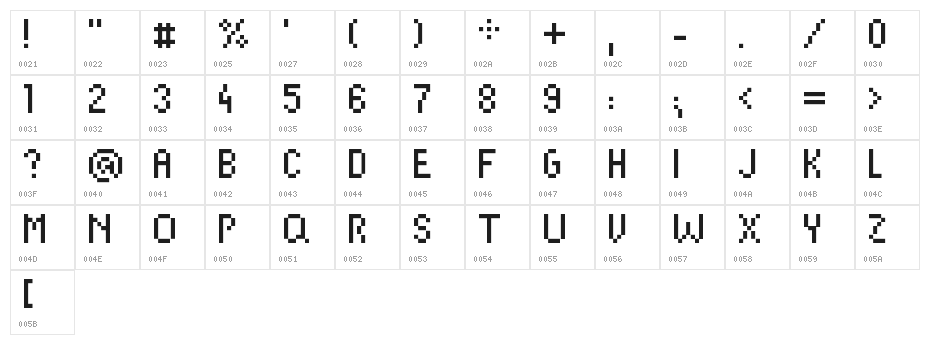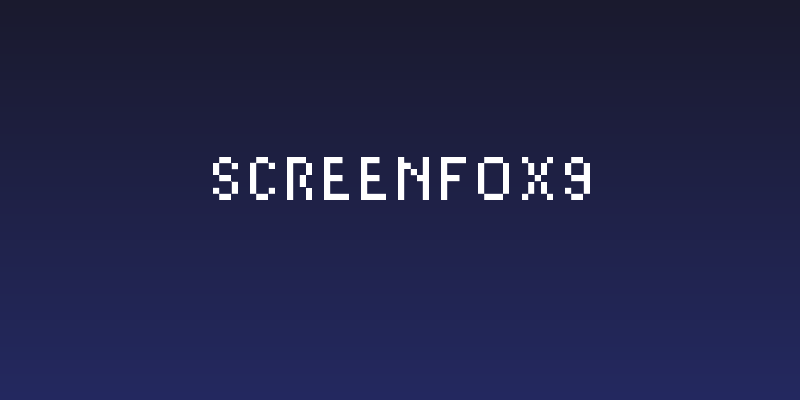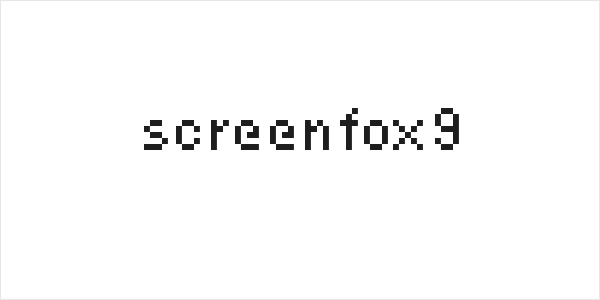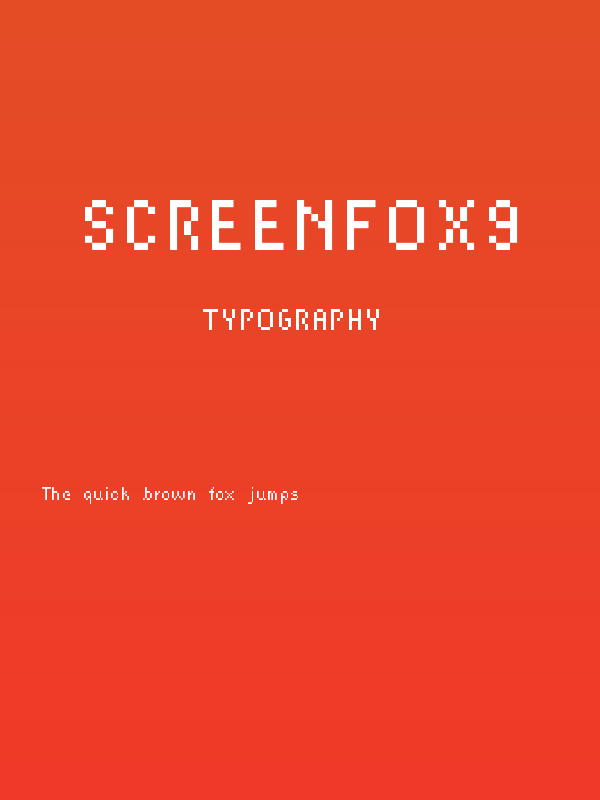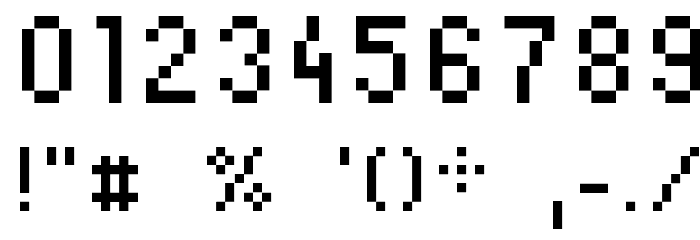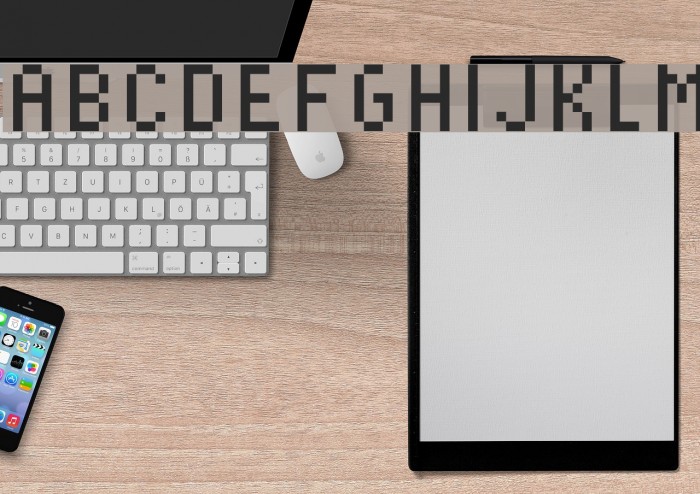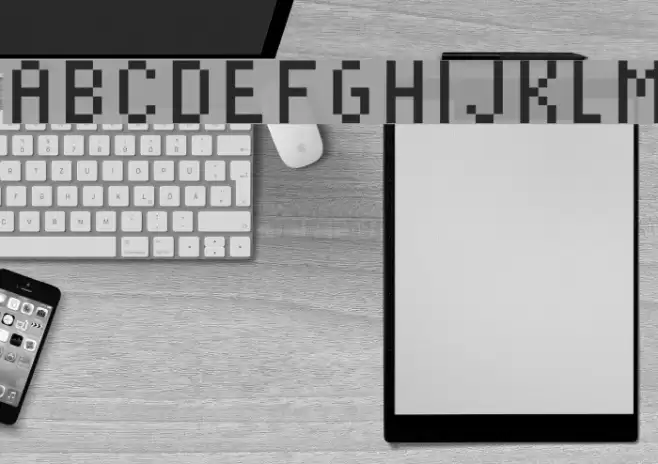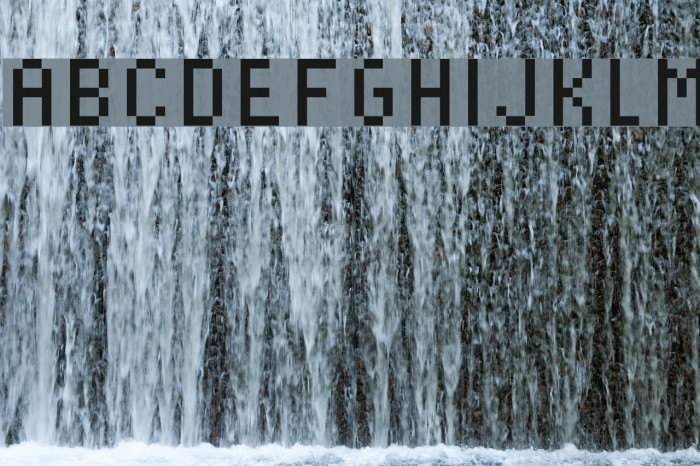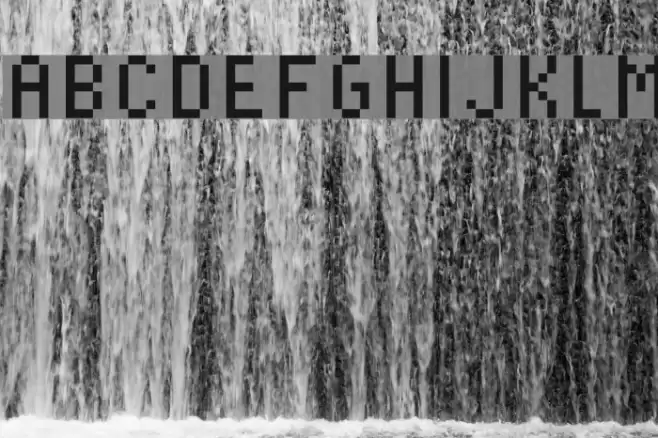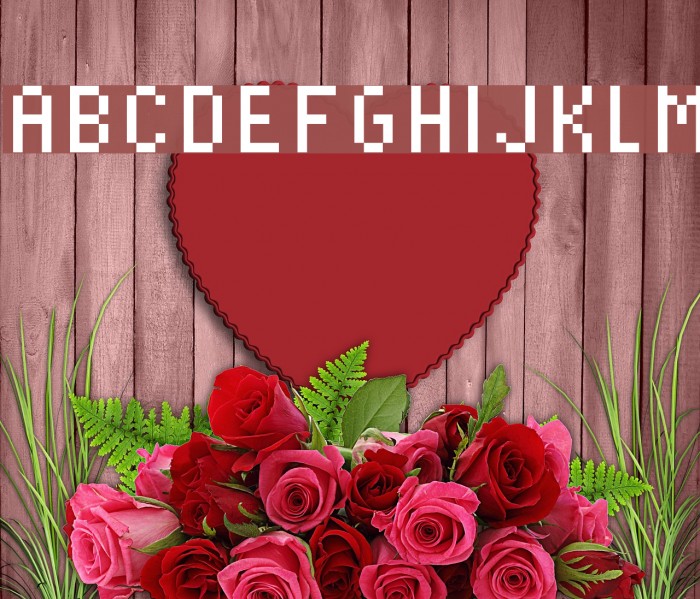
screenfox9 Font
✎ Pixel
| Projets proposés | Ideal for retro video game designs, digital art projects, tech-themed posters, and any creative work that seeks to evoke a sense of nostalgia for early computing. |